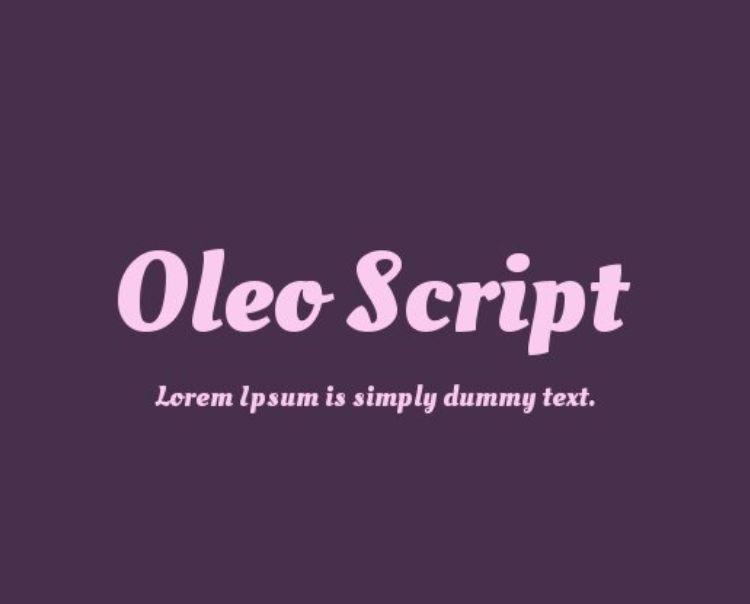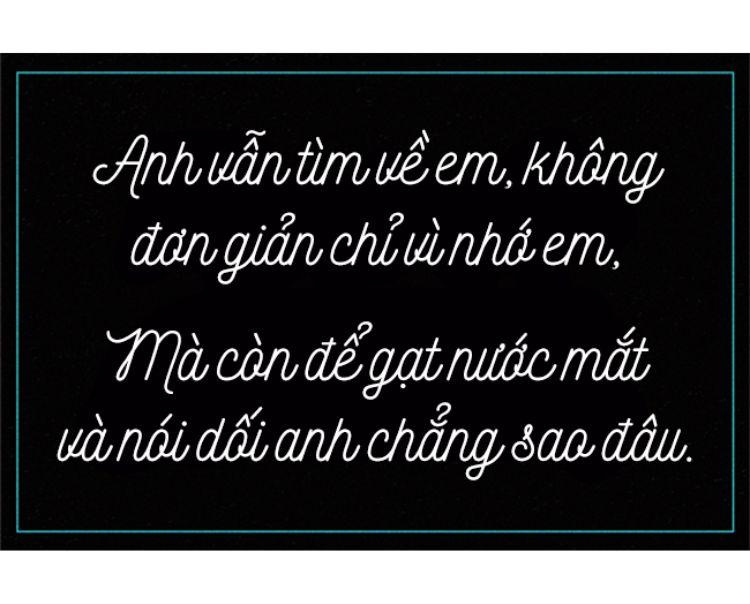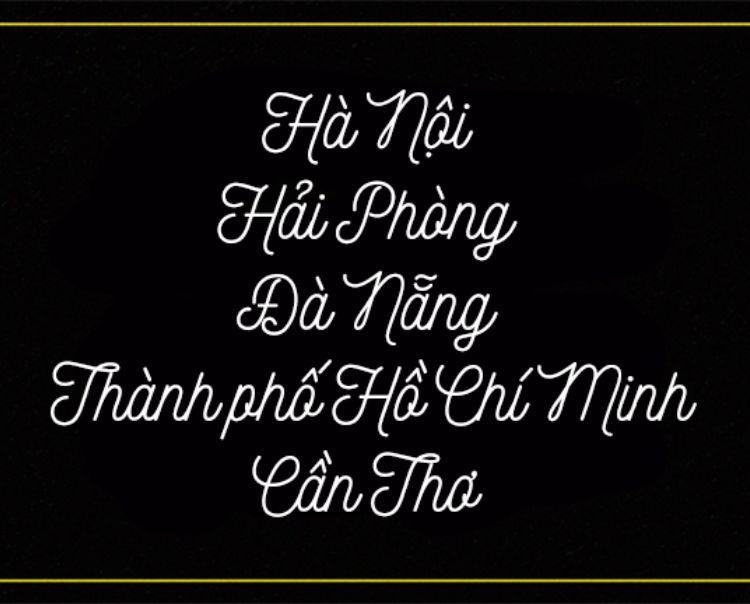
Bạn đang tìm kiếm một font chữ trang trí thanh lịch và lộng lẫy? Vậy thì font chữ calligraphy chính là sự lựa chọn hàng đầu dành cho bạn. Trong bài viết ngày hôm nay, Gitiho sẽ chia sẻ với bạn bộ 10+ font chữ calligraphy đẹp mê hoặc chắc chắn bạn không thể bỏ qua, tất nhiên kèm theo link tải toàn bộ các font chữ ở cuối bài viết.
Vẻ ngoài lộng lẫy, nét chữ viết tay hoa mỹ, khí chất sang trọng, đây là những mô tả ngắn gọn và chính xác nhất về font chữ calligraphy.
Đặc điểm của font chữ này là đường nét cực kỳ mềm mại và thanh thoát, toát lên vẻ sang trọng dù xuất hiện trên bất cứ ấn phẩm nào.
Với tính chất sang trọng và lộng lẫy của mình, font chữ calligraphy sẽ là sự lựa chọn hoàn hảo cho các tấm thiệp mời, thiệp giới thiệu, hay những poster chú trọng vào sự mềm mại và tinh tế. Tuy nhiên, hãy chú ý rằng bản chất font chữ calligraphy là một font chữ đẹp phù hợp để trang trí hơn là để trình bày các văn bản dài. Do đó, nó thường được dùng cho các tiêu đề, đề mục thay vì nội dung ấn phẩm.
Dưới đây là tổng hợp font chữ calligraphy phá cách khác trong trường hợp bạn muốn một làn gió mới cho thiết kế của mình.
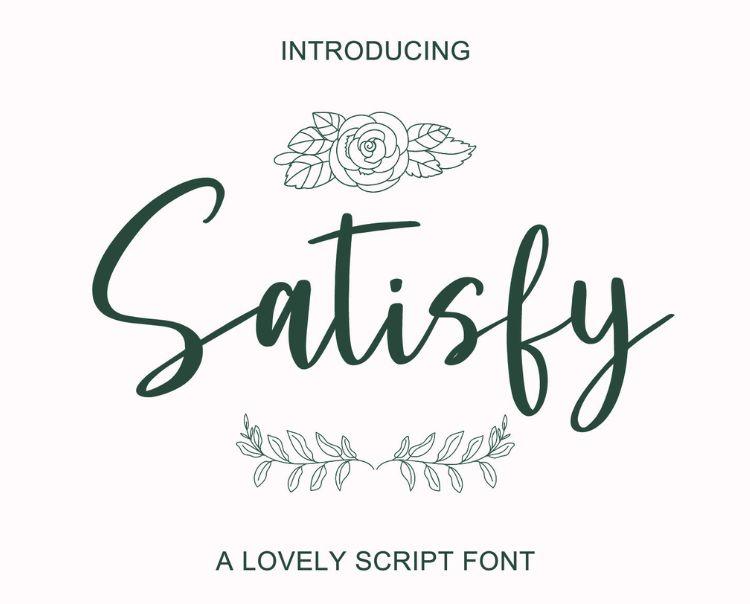
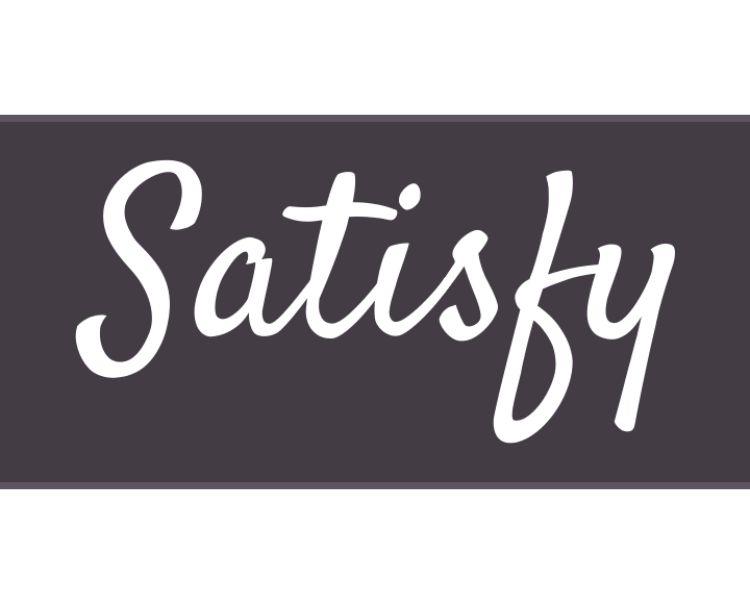
Các font chữ calligraphy đều là những font chữ có tính thẩm mỹ cao, nhưng cũng chính vì sự lộng lẫy của chúng mà bạn có thể sẽ gặp đôi chút khó khăn khi tìm các cặp font chữ phù hợp cho thiết kế của mình. Vậy thì hãy cùng mình tìm ra các giải pháp kết hợp font chữ calligraphy nhé!
Một font chữ calligraphy thanh lịch khi đứng cùng một font chữ có chân (serif font) thời tượng sẽ tạo nên một vẻ ngoài tinh tế và cổ điển cho ấn phẩm. Không ngoa khi nói rằng đây chính là "một cặp trời sinh" khi cả 2 font chữ có thể bổ trợ cho nhau cực kì ăn ý.
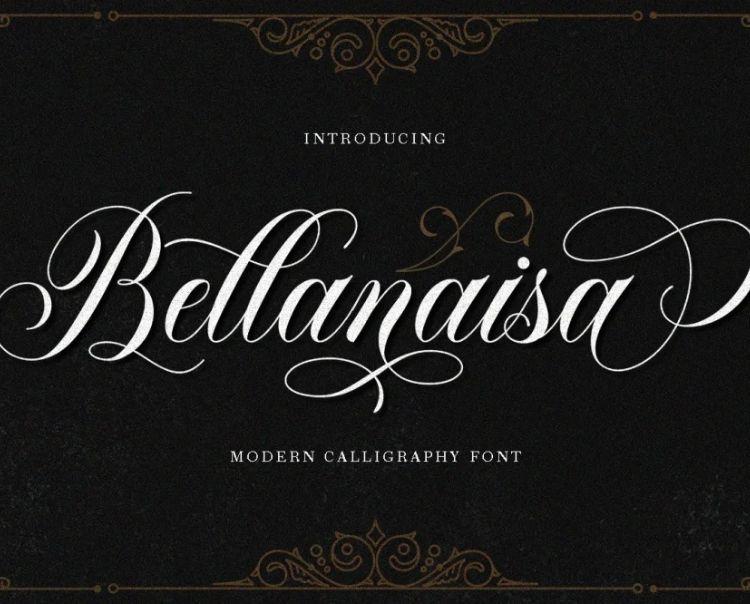
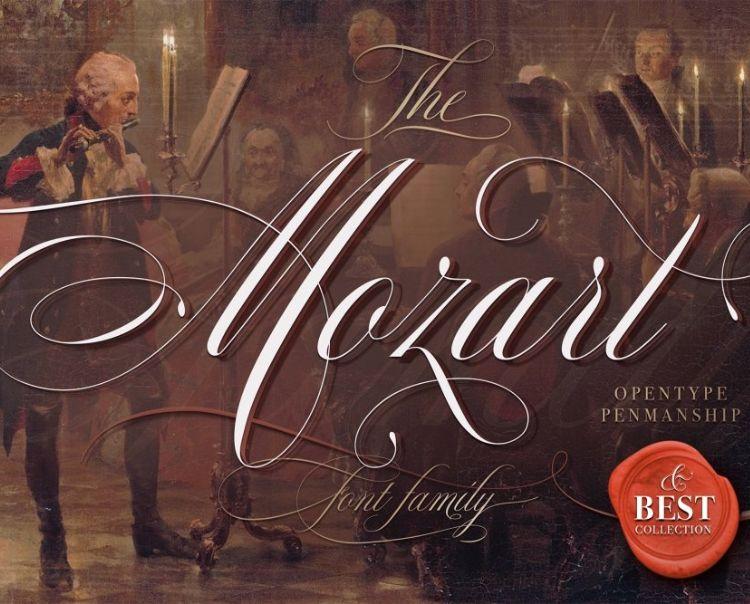
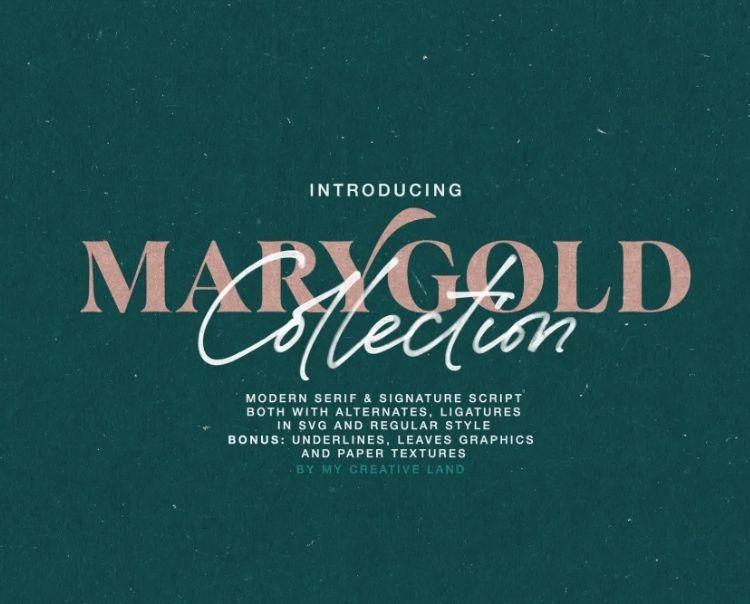
Nếu như sự kết hợp của một font chữ calligraphy và một font chữ có chân tạo nên nét cổ điển cho thiết kế thì phép cộng của một font chữ calligraphy và một font chữ không chân (san serif font) sẽ cho ra kết quả là sự phá cách và trẻ trung. Khi sử dụng cặp font này, bạn hãy lưu ý chọn font chữ không chân tối giản và nét mảnh để ăn nhập với những nét chữ mềm mại và linh hoạt của font chữ calligraphy nhé.
Nếu bạn đang bí ý tưởng thì dưới đây là một vài gợi ý cho bạn nếu hướng đến sự mới mẻ và độc đáo cho thiết kế của mình.